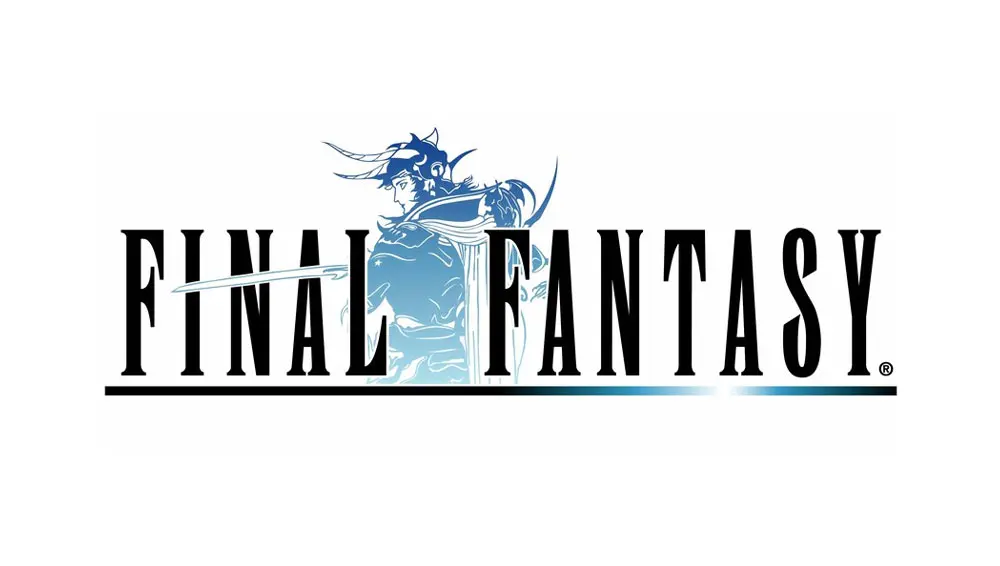
Anime text font: una información
El entorno del anime está lleno de magia, aventura y, por supuesto, estilos tipográficos únicos. Si alguna vez te has preguntado qué tipografía da ese toque distintivo a tus series favoritas, estás en el lugar correcto. Exploraremos el maravilloso entorno de las fuentes de anime, desde las clásicas hasta las más modernas, y te ayudaremos a encontrar la perfecta para tus proyectos.
¿Qué hace que una fuente sea ideal para anime?
Las fuentes de anime a menudo se caracterizan por su versatilidad. Pueden ir desde lo elegante y sofisticado hasta lo desenfadado y lúdico, reflejando la amplia gama de géneros y estilos presentes en el anime. Algunos elementos clave que definen una fuente de anime incluyen:
• Legibilidad: Aunque la estética es importante, la legibilidad es clave, especialmente para subtítulos o títulos.
• Estilo: Desde lo gótico y oscuro hasta lo limpio y minimalista, la elección del estilo depende del proyecto.
• Personalidad: Una buena fuente de anime debe transmitir la personalidad y el tono del trabajo al que acompaña.
Fuentes Inspiradas en el Anime
Existen numerosas fuentes que capturan la esencia del anime, aunque no todas estén explícitamente diseñadas para ello. A menudo, las fuentes con un toque retro, japonés o con elementos distintivos, como serifas o sans-serif, se utilizan con gran éxito. Algunas familias tipográficas populares incluyen:
• Fuentes con estética retro: Estas recuerdan a los videojuegos y series de anime de los 80 y 90. Suelen ser pixeladas o con una apariencia ligeramente tosca, que añade un encanto nostálgico.
• Fuentes con rasgos japoneses: Algunas fuentes incorporan caracteres japoneses o elementos de caligrafía japonesa, aportando autenticidad.
• Fuentes góticas: Ideales para proyectos oscuros o con temas sobrenaturales, ofrecen un toque dramático y elegante.
• Fuentes minimalistas: Perfectas para diseños modernos y limpios, transmiten sencillez y sofisticación.
Final Fantasy y su icónica tipografía
La saga Final Fantasy es un ejemplo emblemático de cómo una fuente de anime puede contribuir al éxito de una franquicia. El logo de Final Fantasy utiliza la fuente "Enge Etienne", diseñada por Opti Font. Esta fuente, con su estética retro y elegante, se ha convertido en un icono reconocible a nivel mundial. Su popularidad se extiende más allá de los videojuegos, encontrándose en otros ámbitos como películas de ciencia ficción japonesa.
Nombre de la Fuente Estilo Adecuado para
Enge Etienne Retro, elegante Logos, títulos, videojuegos
La elección de la fuente Enge Etienne en Final Fantasy no fue accidental. Su diseño, que recuerda a las fuentes de los años 80, contribuyó a crear la atmósfera retro y nostálgica de la saga. La decisión reflejó la intención de los diseñadores de crear un estilo atemporal que trascendiera las modas pasajeras.
Consejos para Elegir la Fuente Adecuada
Elegir la fuente de anime adecuada requiere considerar varios aspectos:
• Género del anime: Una fuente gótica puede ser ideal para un anime de terror, mientras que una fuente limpia y moderna podría ser más apropiada para una comedia romántica.
• Público objetivo: Considera la edad y los gustos de tu público a la hora de seleccionar la fuente.
• Plataforma: Asegúrate de que la fuente sea legible en diferentes plataformas y dispositivos.
• Legibilidad: Prioriza la legibilidad sobre la estética. Una fuente ilegible arruinará la experiencia del usuario.
La elección de la fuente de anime correcta es crucial para crear una experiencia visual atractiva y coherente. Considera los consejos y recursos mencionados para encontrar la fuente perfecta que complemente tu trabajo y cautive a tu audiencia.